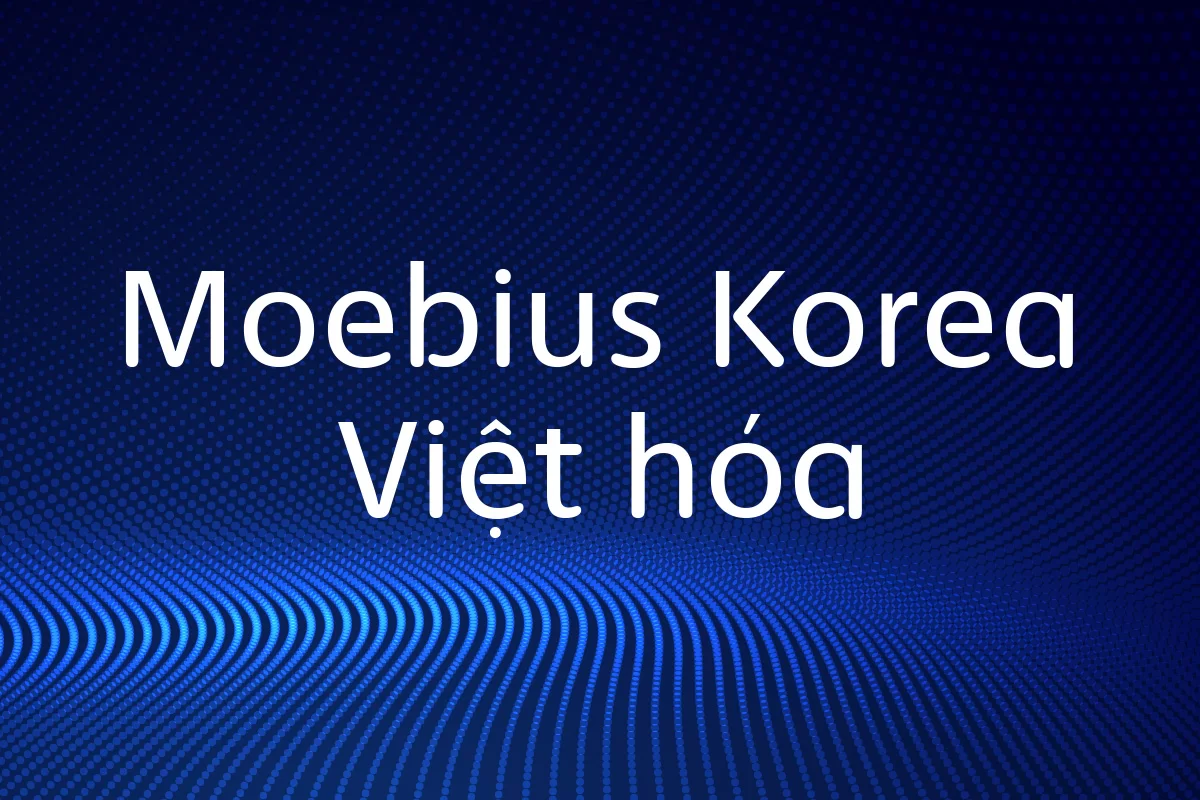
Moebius Korea là một font chữ sans-serif mang hơi thở tối giản, hiện đại với những đường nét tròn trịa, thanh thoát. Khi được Việt hóa, font giữ nguyên tinh thần trẻ trung và thân thiện, đồng thời hỗ trợ đầy đủ dấu tiếng Việt để sử dụng linh hoạt trong thiết kế. Moebius Korea đặc biệt phù hợp cho các dự án thương hiệu, quảng cáo, giao diện web và app nhờ tính dễ đọc và vẻ ngoài cân đối. Nét chữ mềm mại nhưng vẫn vững chắc giúp font này vừa thích hợp làm tiêu đề nổi bật, vừa dùng tốt cho đoạn văn dài. Đây là lựa chọn lý tưởng cho những ai yêu thích sự tinh gọn nhưng không khô cứng trong thiết kế chữ.